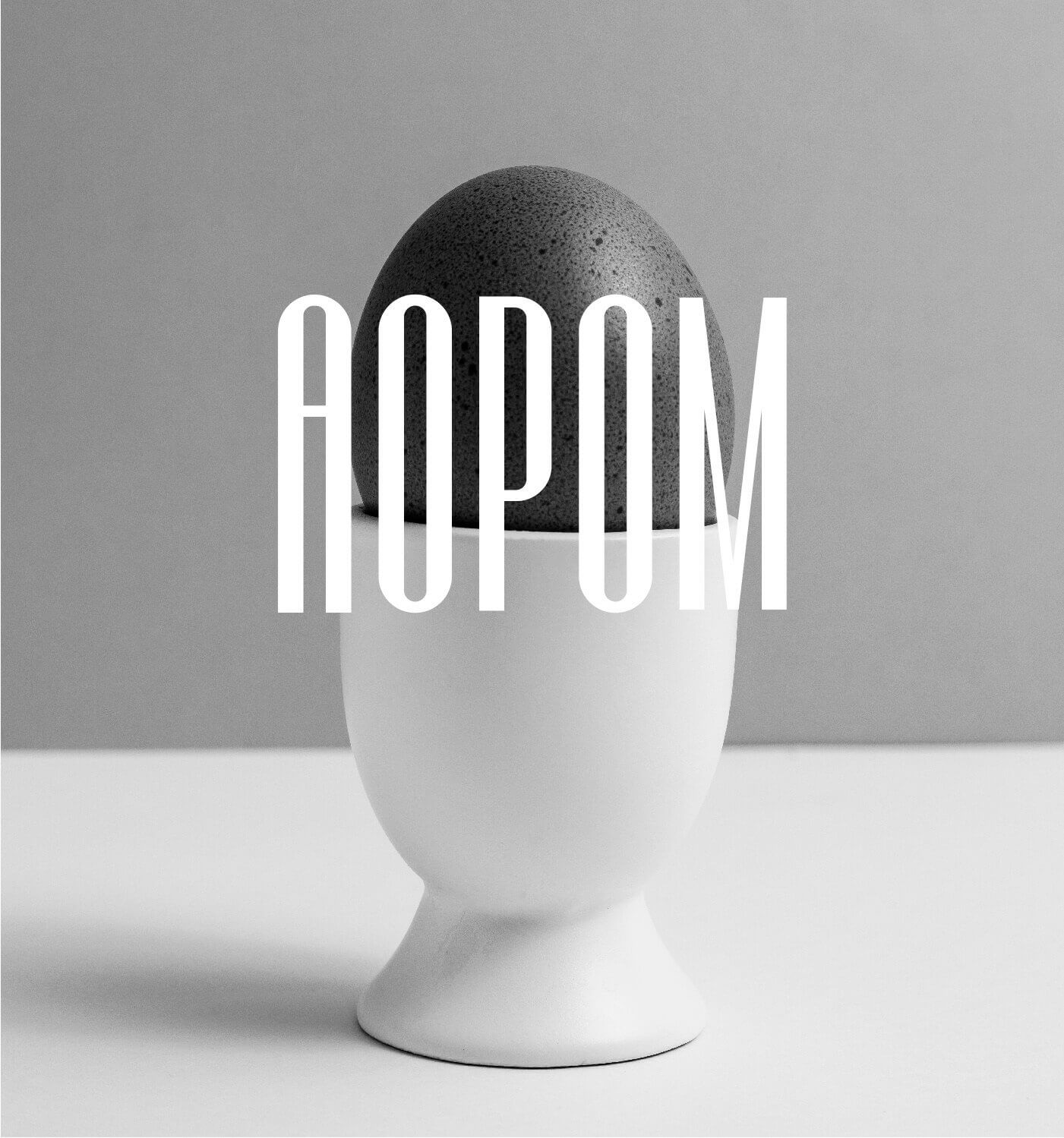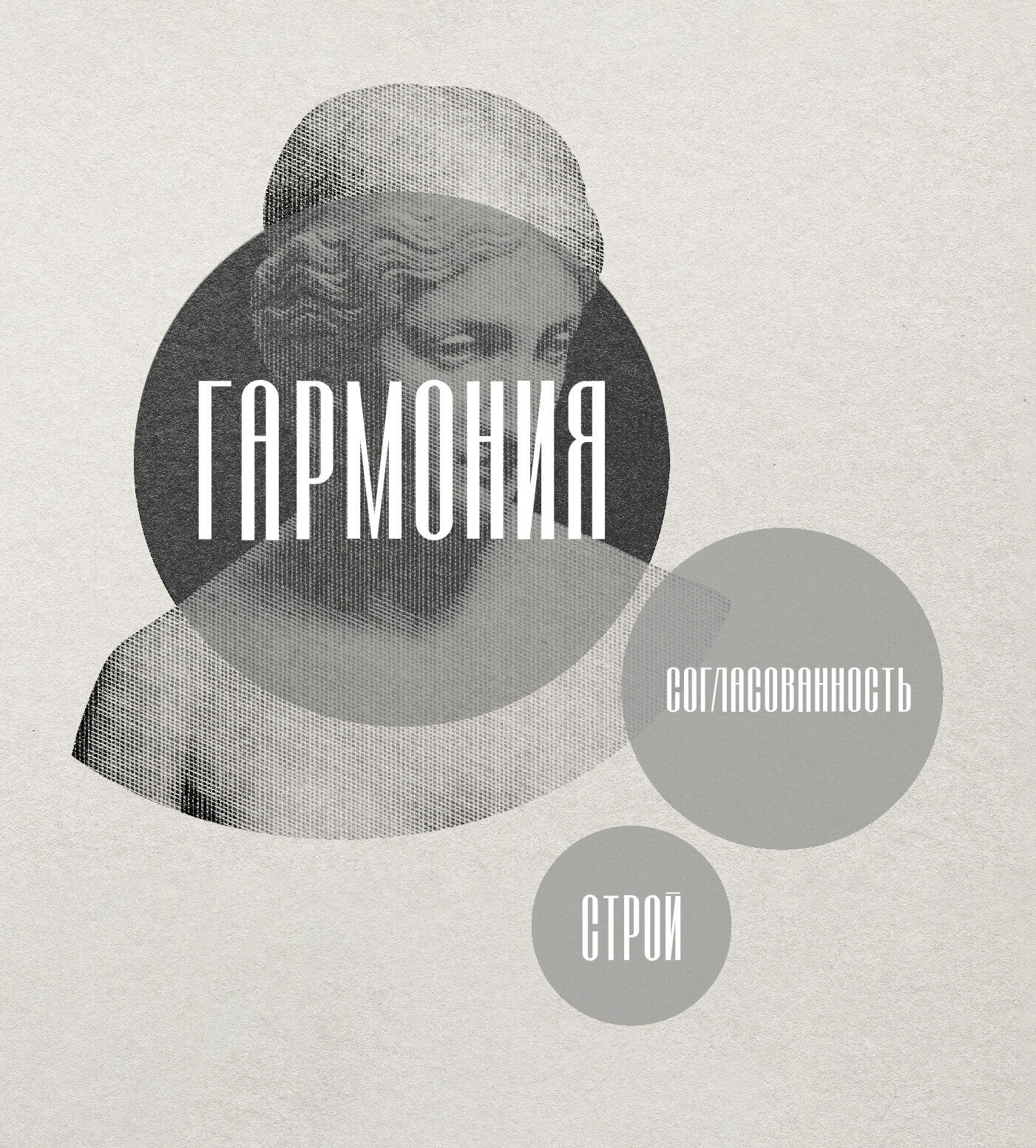
Дополнения Шрифты Татьяна Гапонова 20 октября 2022 Шрифт АОРОМ (Кириллица) Строгий декоративный шрифт АОРОМ построенный на основе спирали золотого сечения. Формат - OTF, TTF. Размер - 2 мб. Автор: Dion Сhunon Скачать Шрифт АОРОМ (Кириллица)